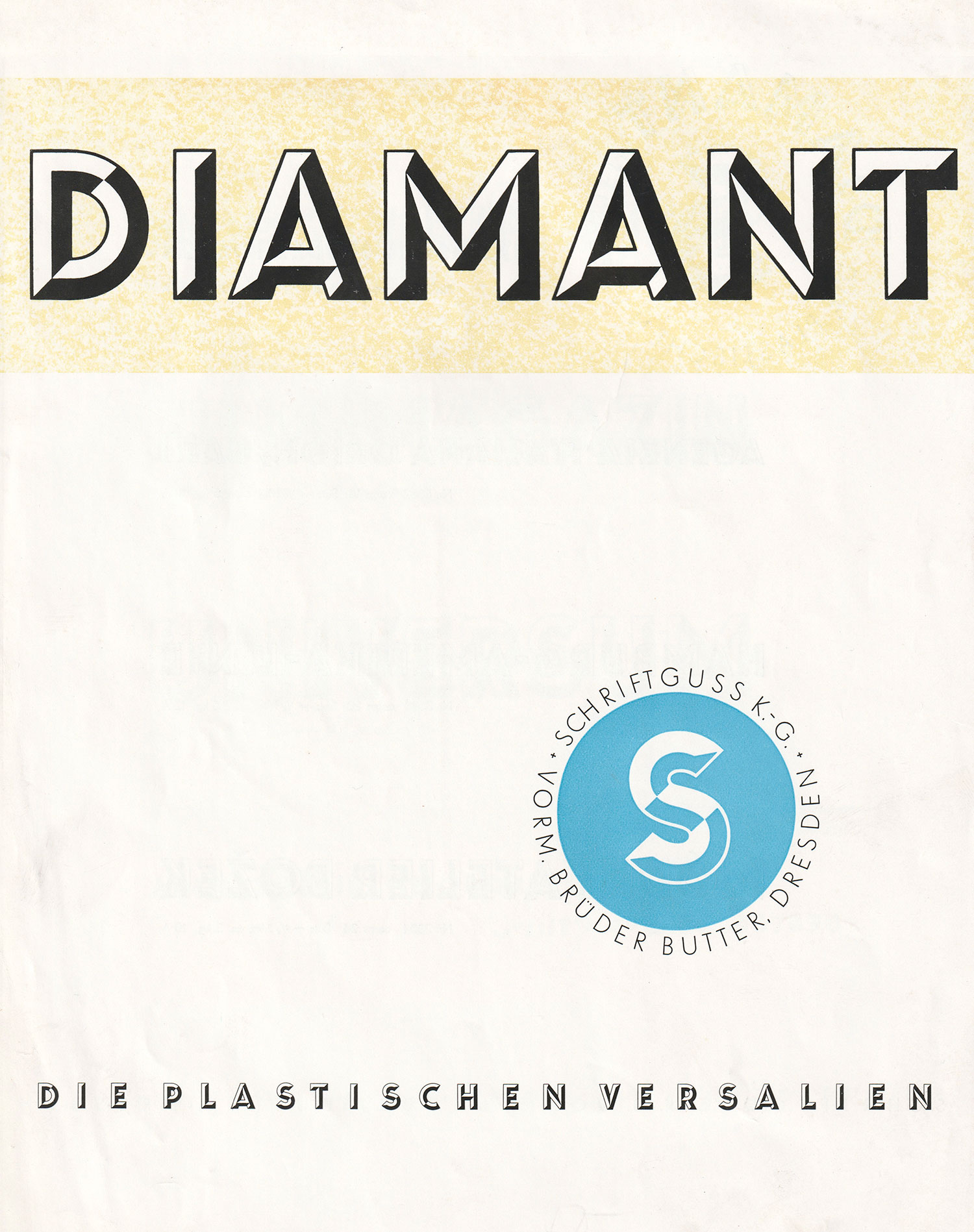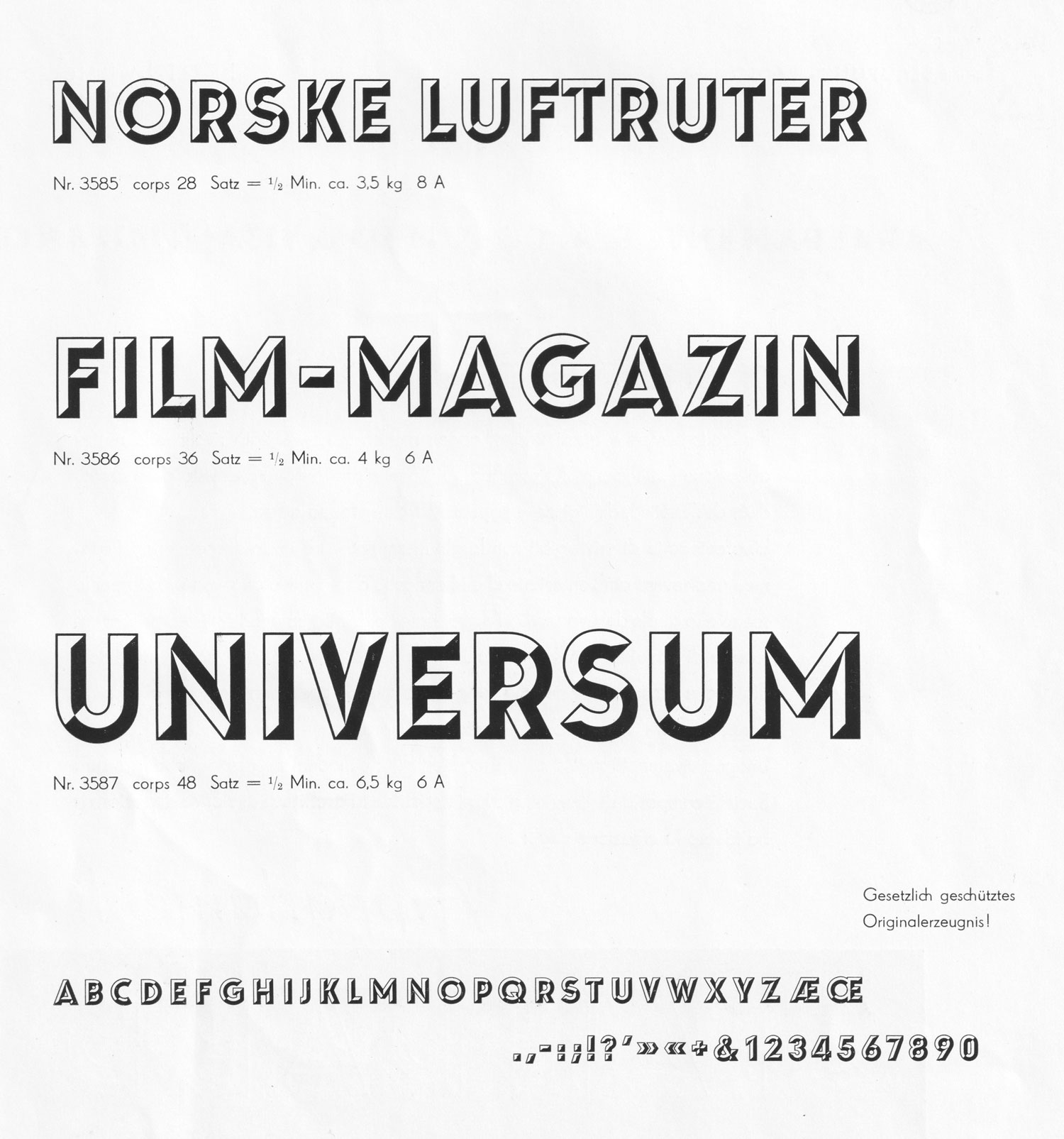
Die Diamant von Johannes Lehmann erschien 1937 bei der Schriftguß KG. Die Schrift verfügt ausschließlich über Versalien.
Eine Digitalisierung von RMU Fonts erschien 2015 unter dem Namen Plastica in zwei Versionen. Die Pro-Version enthält neben einer lateinischen Belegung auch Kyrillisch und Griechisch.